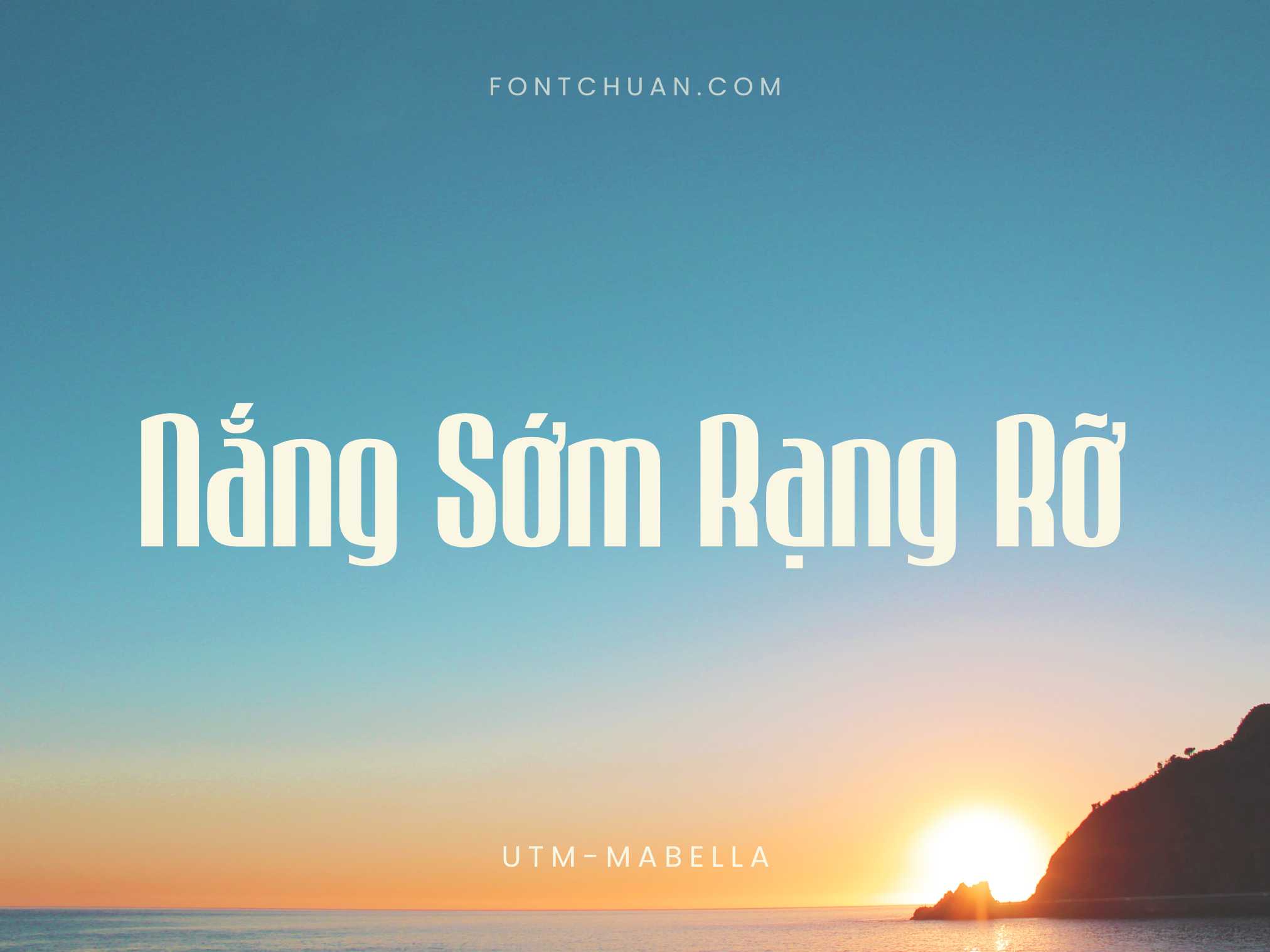
Font UTM Mabella Việt Hóa
UTM Mabella là một font chữ mang phong cách hiện đại, thanh lịch với các đường nét mềm mại và tinh tế. Font này được thiết kế để tạo sự sang trọng và chuyên nghiệp trong các thiết kế thương hiệu và ấn phẩm đồ họa. Font đã được Việt hóa bởi Thiên Minh, hỗ trợ đầy đủ tiếng Việt cùng hơn 200 ngôn ngữ khác, giúp mở rộng khả năng ứng dụng. Thành viên của Font Chuẩn đã sưu tầm và giới thiệu font này nhằm đáp ứng nhu cầu bạn đọc, cung cấp nguồn tham khảo chất lượng và ứng dụng thực tế vào các dự án thiết kế
Về đặc điểm thiết kế, UTM Mabella có các đường nét mềm mại, độ tương phản nhẹ và phong cách tinh tế. Font này phù hợp với nhiều ứng dụng như thiết kế logo, thiệp mời, biển hiệu, tiêu đề trang web và các ấn phẩm sáng tạo. Các ngành nghề như quảng cáo, ẩm thực, thiệp cưới và giáo dục có thể tận dụng font này để tạo điểm nhấn và mang đến sự thanh lịch trong các sản phẩm thiết kế